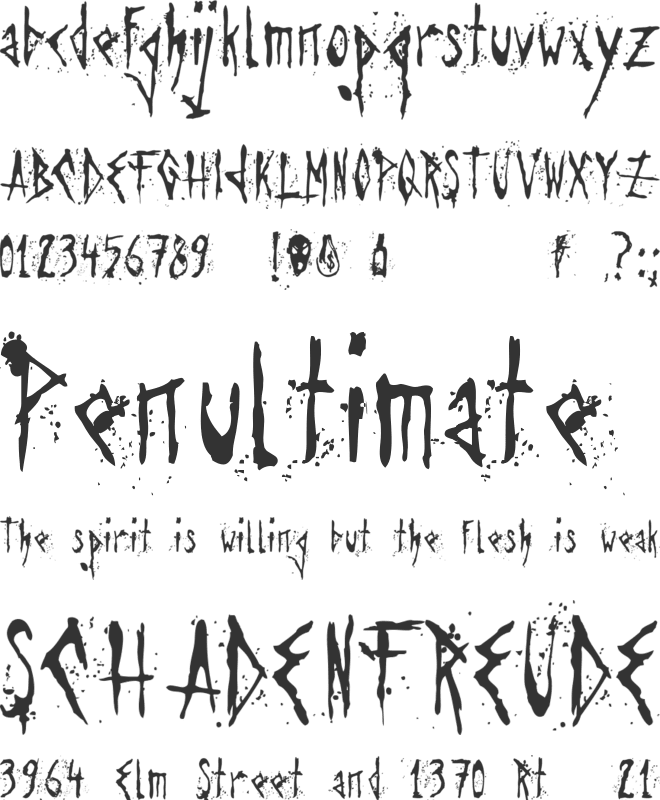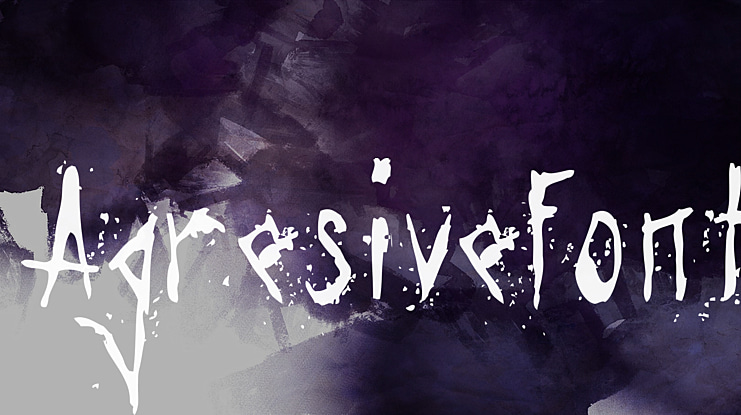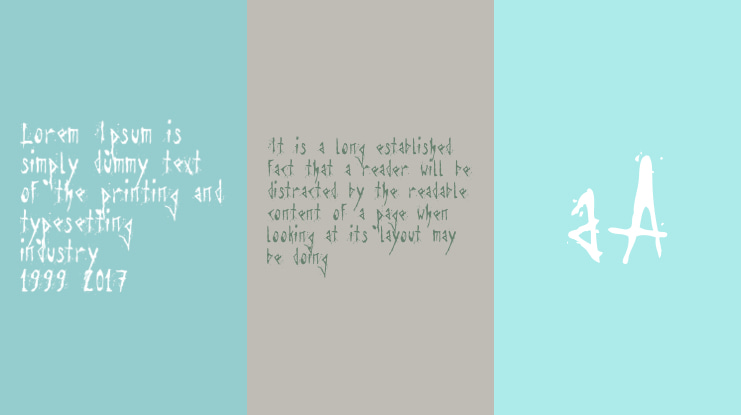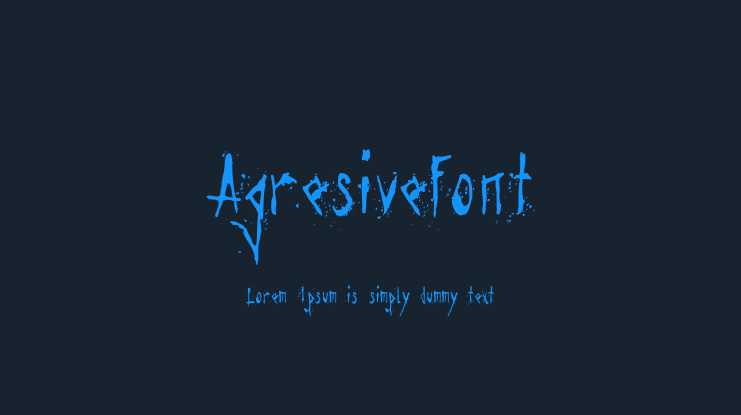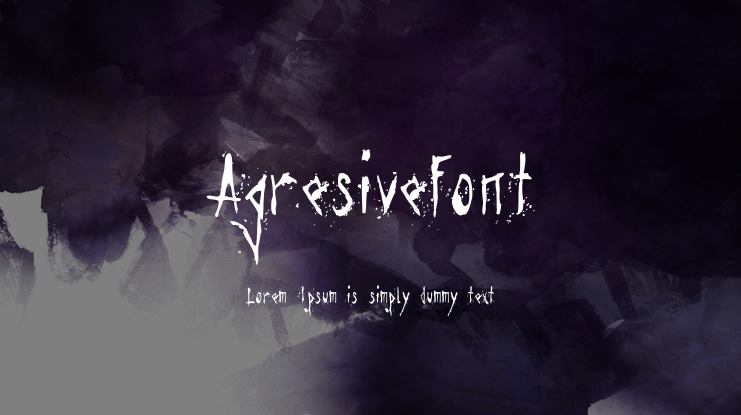
Agresivefont Font
Tipografía gestual diseñada para textos a los que se les quiera dar atibutos de agresividad y violencia. Se deberá usa en titulares o textos de gran tamaño por su escasa legibilidad en cuerpos pequeños.